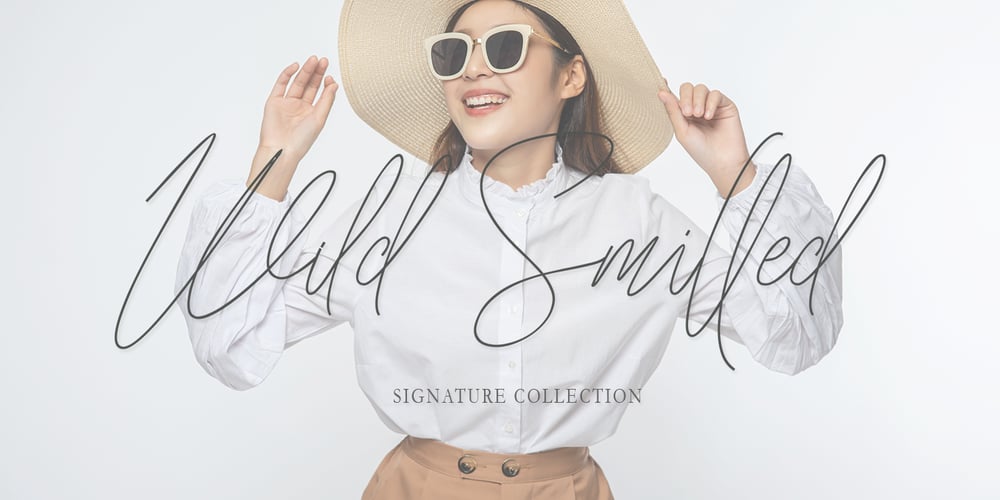
Wild Smilled Font Family was designed by Ikhsan Maulana and published by IM Studio. Wild Smilled contains 2 styles and family package options. Wild Smilled adalah skrip yang ramping dan khas yang akan memberikan kelas dan gaya instan pada pekerjaan Anda. Gunakan font ini untuk pencitraan merek, logo, tanda tangan, undangan, dan semua proyek indah Anda lainnya.Terimakasih.